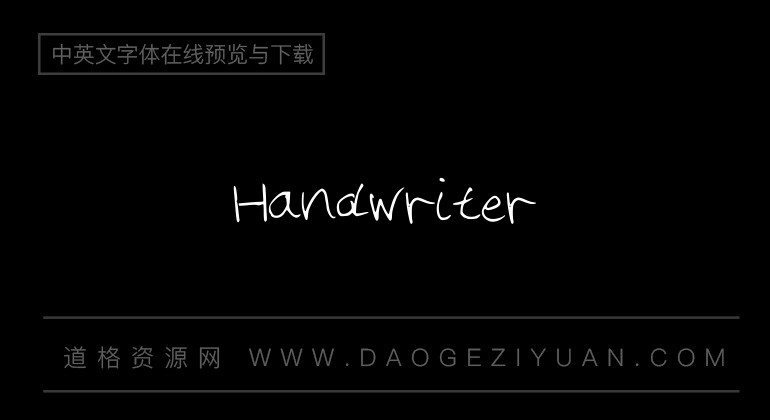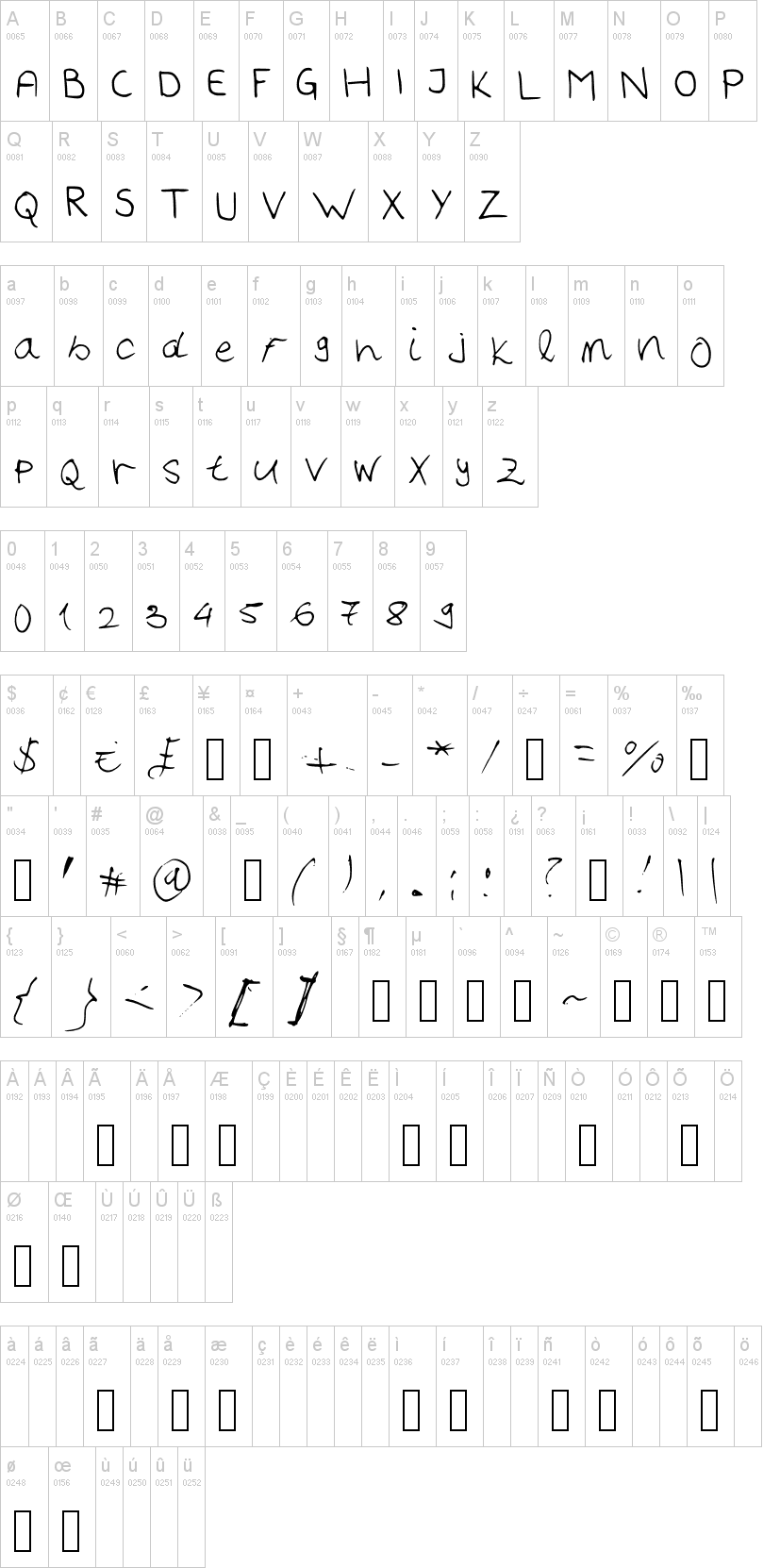
Handwriter 字体是一种手写风格的字体,它可以让文字看起来更加自然,更具表达力。它采用了类似手写的笔画,使得文字更加生动有趣。它可以用于创建海报、名片、招聘等各种文字图形,以及创作简短的文字。它可以让文字更加有趣,更具表现力,给人以温暖的感觉。内容介绍
Handwriter是一款非常不错的手写艺术字体,具有很好的视觉感,适合于文化类的宣传设计、商业类品牌的广告和产品包装设计以及个性化文字排版等较多场景。